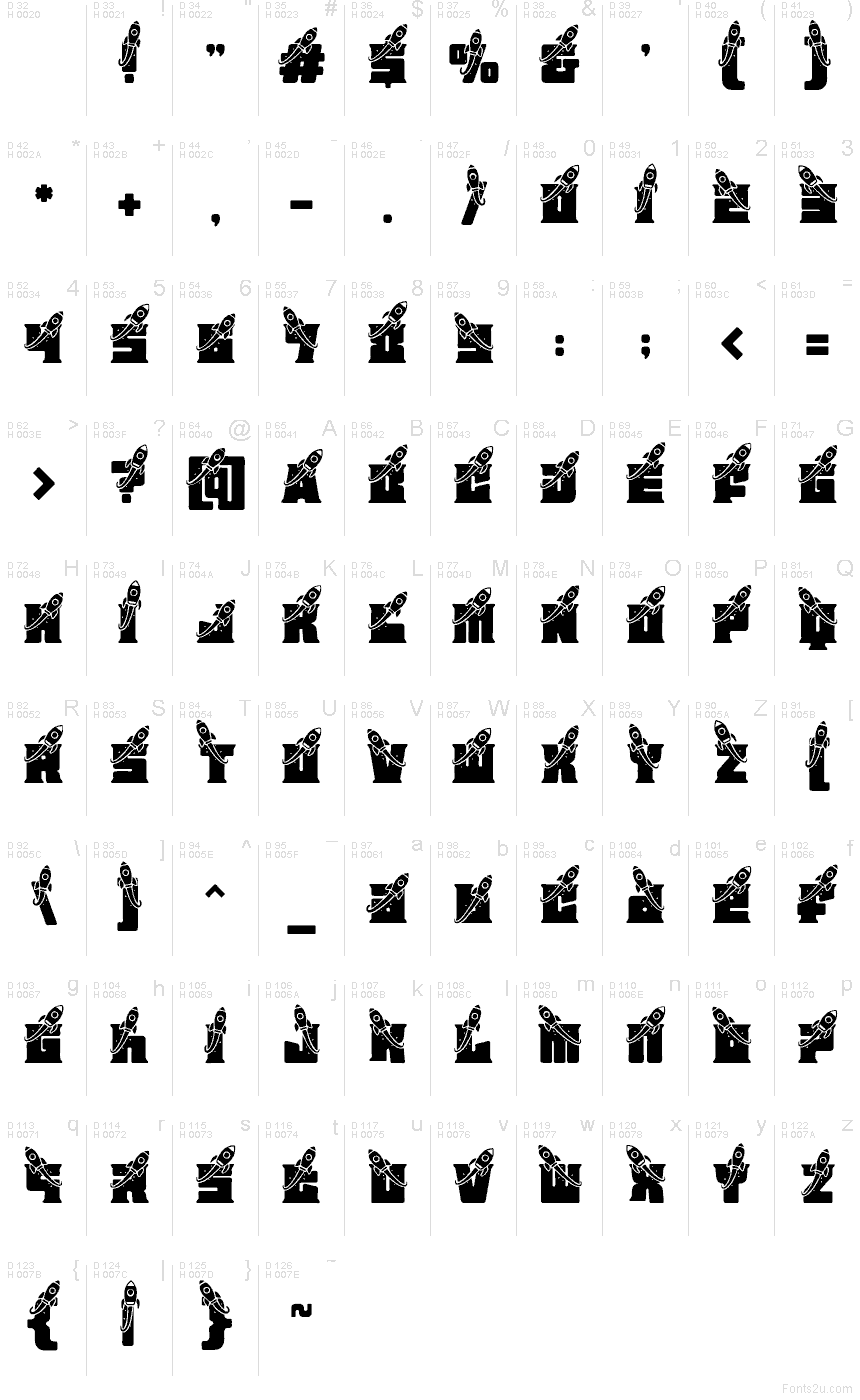
Astral Zenith Six od studia Putracetol je bezplatné písmo typu display s vesmírnou tematikou, kde každé písmeno obepíná dráha obíhající rakety. Tento opakující se motiv orbity dodává designu charakter a mění písmo v malý sci-fi výjev namísto běžného dekorativního stylu.
Je to přirozená volba pro obálky dětských knih, plakáty na vědecké akce, letáky na vesmírné tábory, školní štítky a tematické pozvánky na oslavy. Protože se raketa a zakřivená dráha v písmu opakují, skvěle poslouží i v krátkých logotypech nebo grafice pro sociální sítě, kde má samotný nápis nést atmosféru vesmíru.